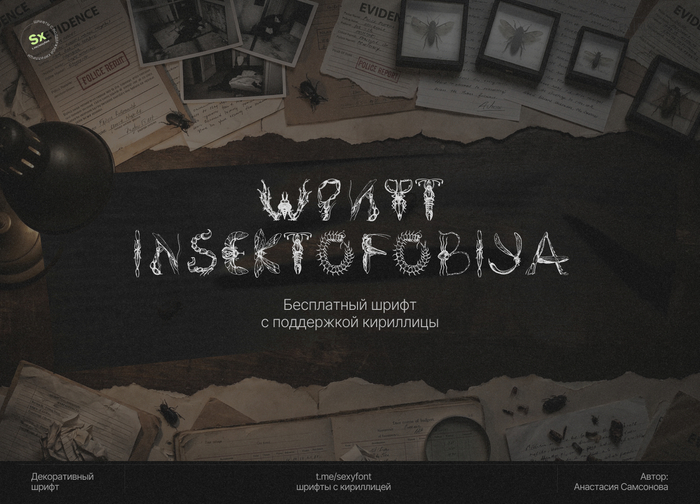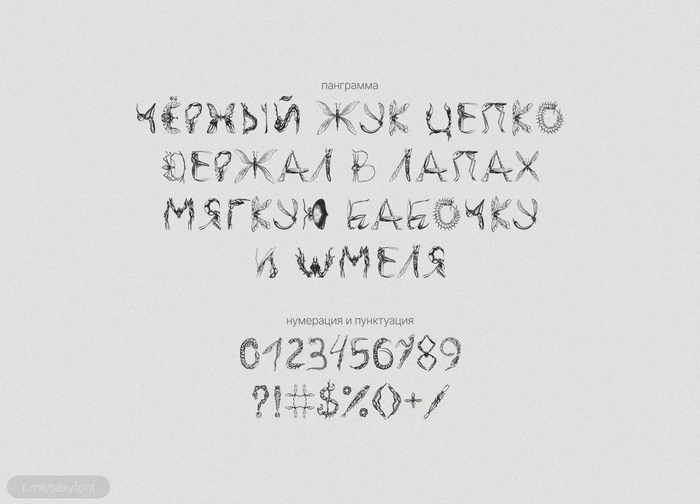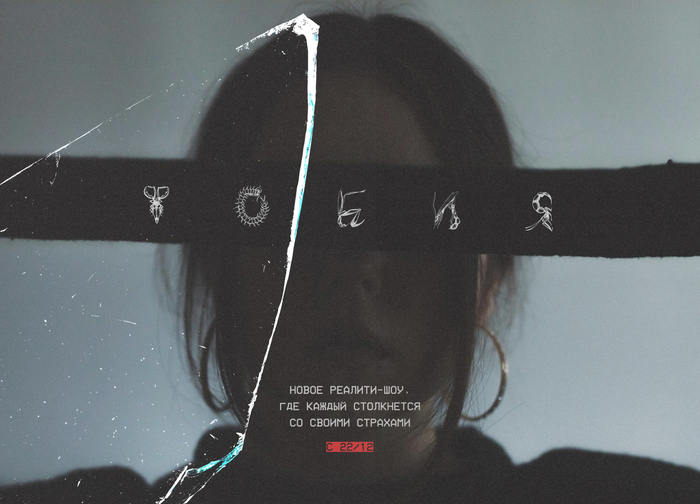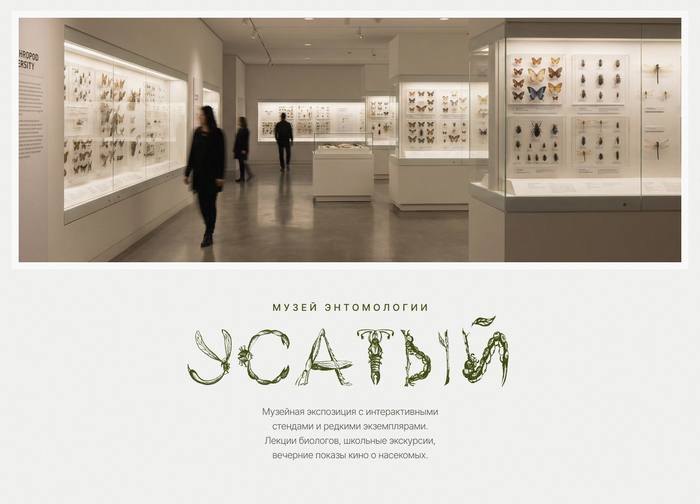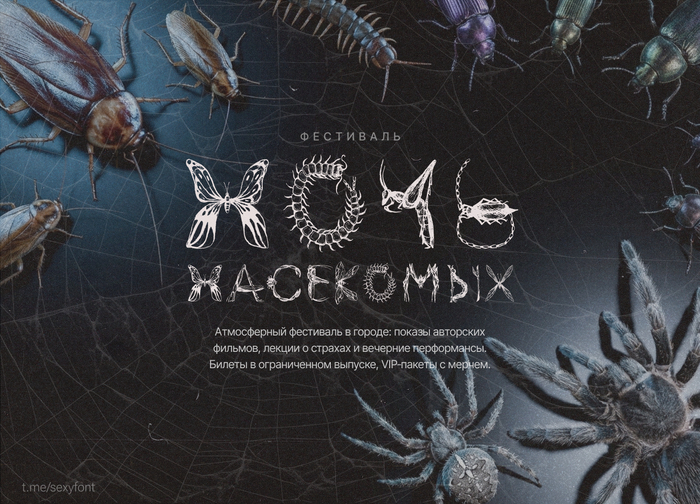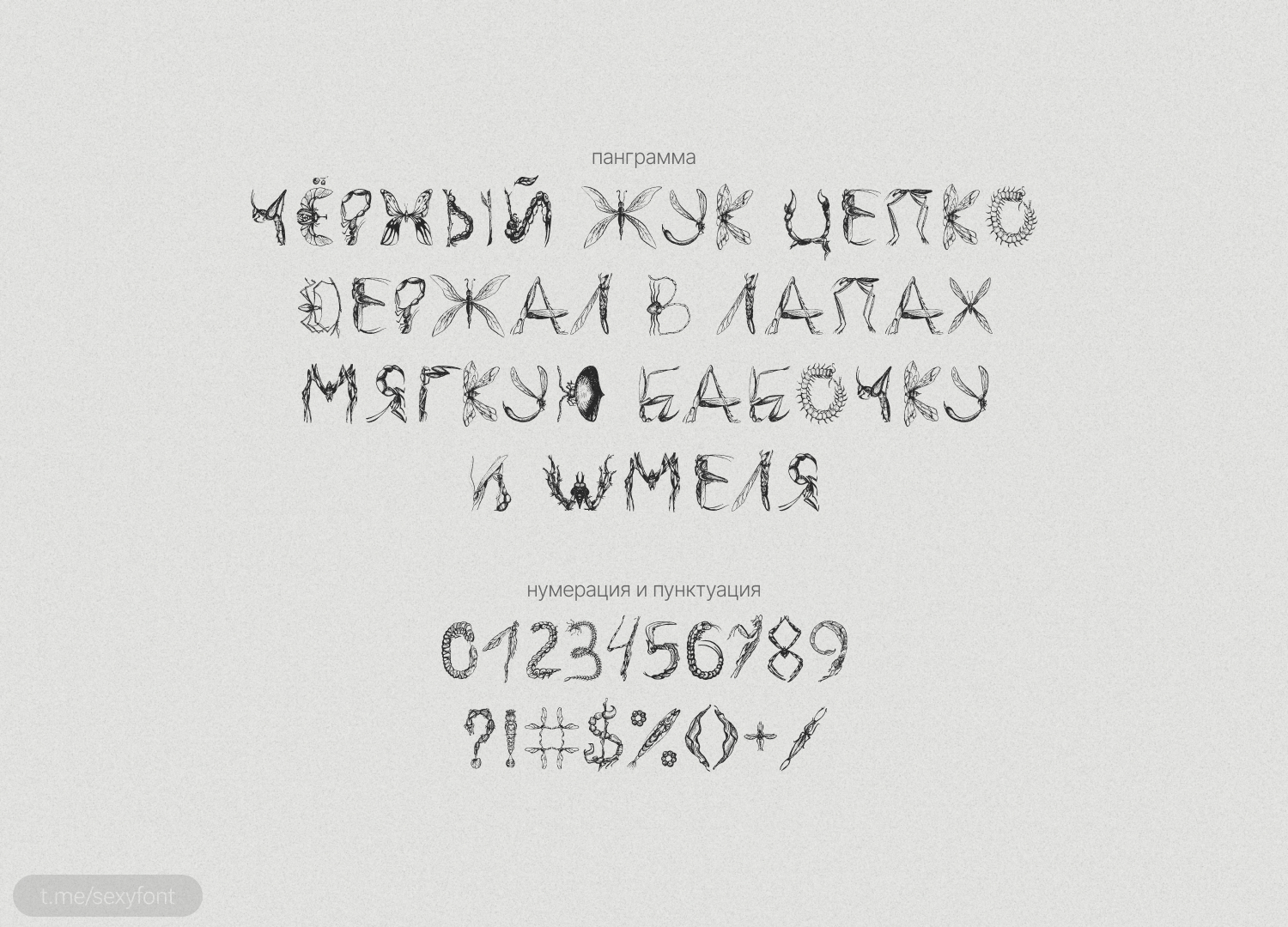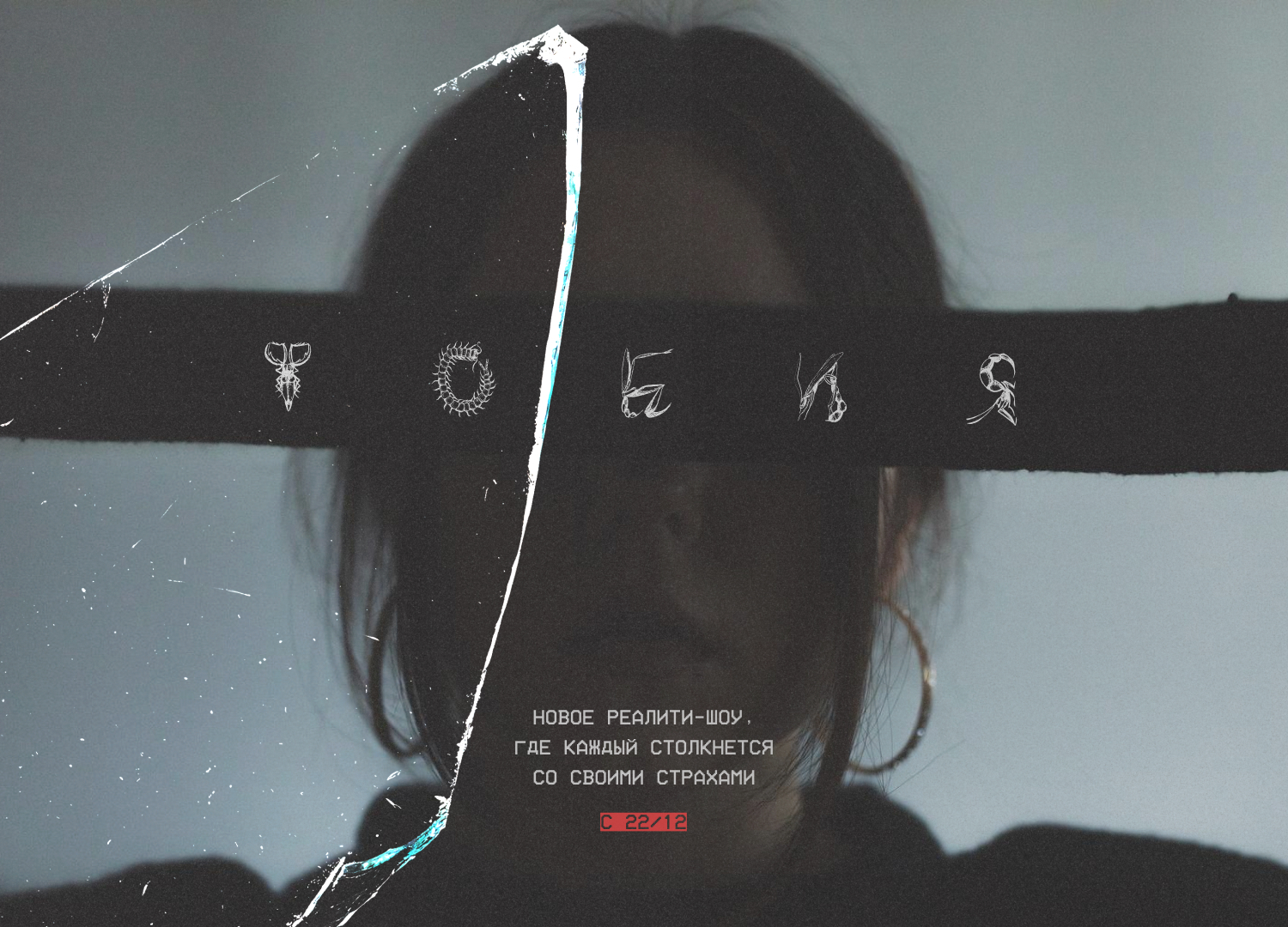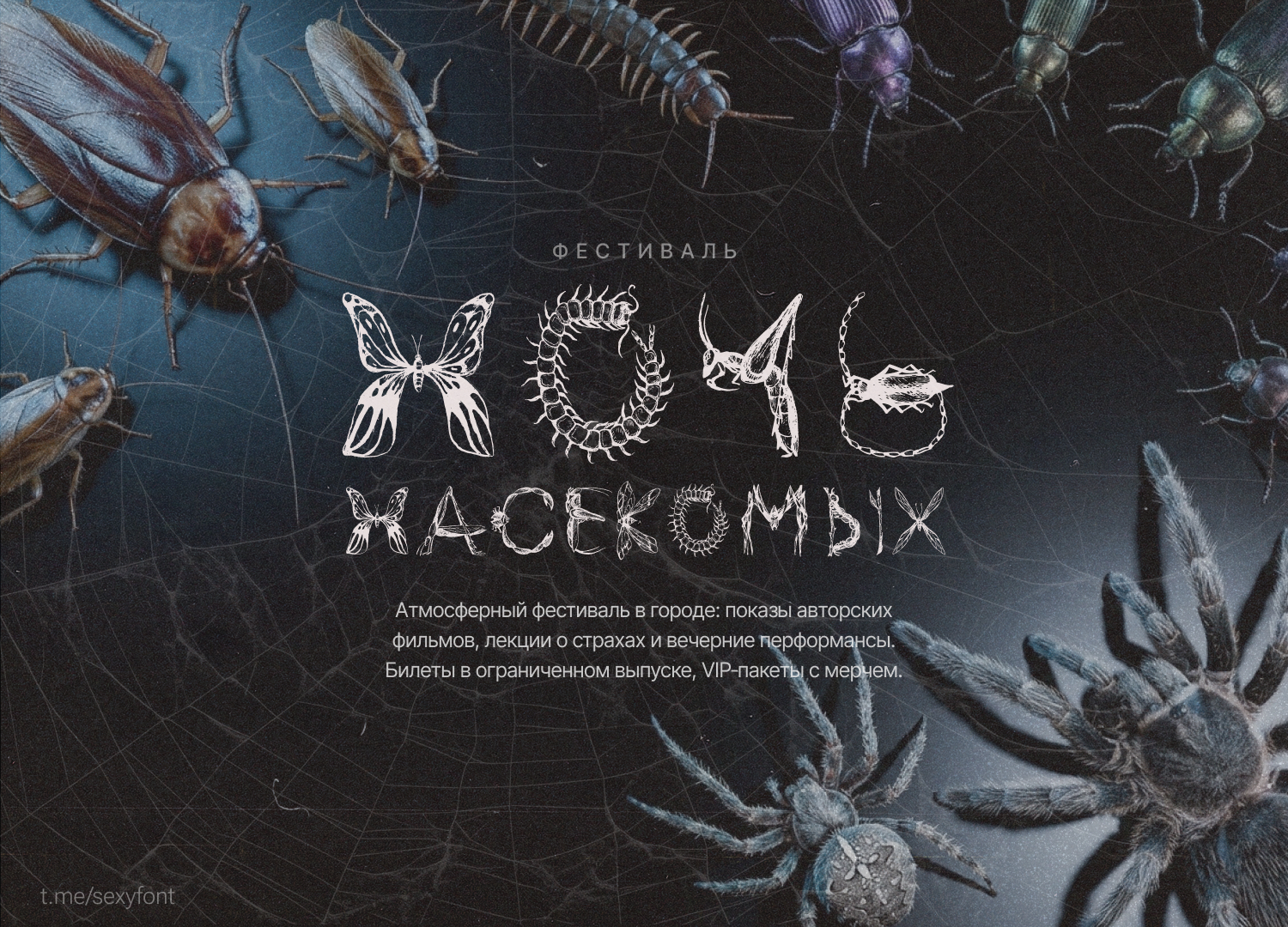
Шрифт Insektofobiya
Insektofobiya. Шрифт для тех, кто хочет, чтобы текст ползал 🪳Буквально. Каждая буква сделана из жуков, пауков и прочих товарищей с шестью лапами. Бесплатный, есть кириллица, вызывает лёгкую панику у людей со слабыми нервами.Идеален для хоррор-постеров, обложек книг и пугания дизайнеров с энтомофобией.Автор: Анастасия Самсонова (спасибо, что создала это)